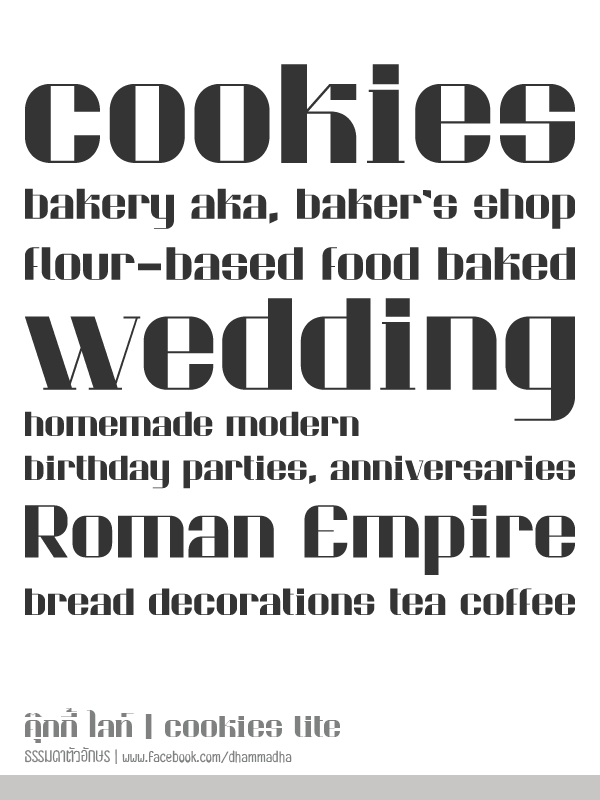
คุ๊กกี้ ไลท์ (cookies lite)
มีช่วงหนึ่ง มีชีวิตวนเวียนอยู่กับเมนูร้านขนม ร้านกาแฟฮะ แล้วก็ผุดฟอนต์ชุดนี้ขึ้นมา …จบแล้ว สั้นไปไหม
ตัวอย่างของฟอนต์ชุด “คุ๊กกี้” ชุดปกติ
ซึ่งชุดไลท์ สามารถใช้งานภาษาไทยได้ครบถ้วน เหมือนชุดปกติครับผม